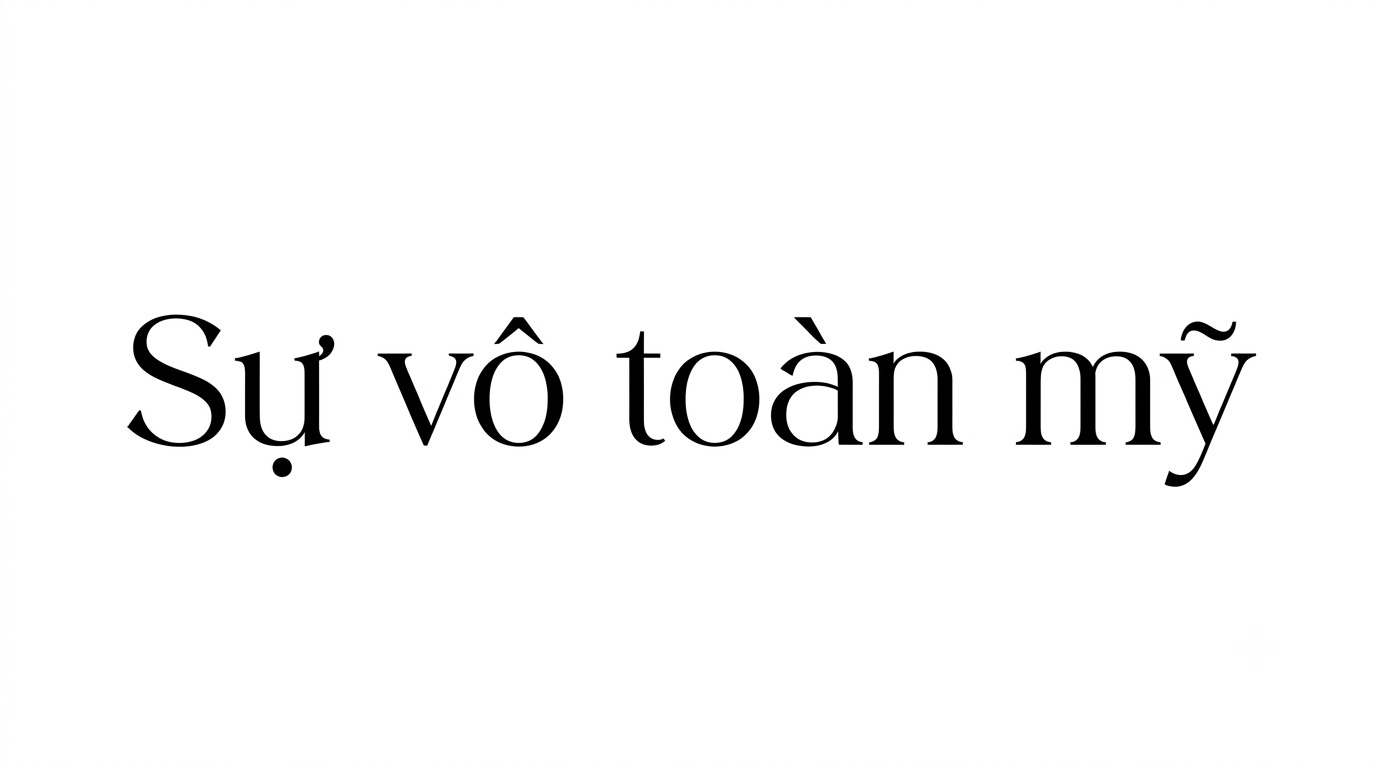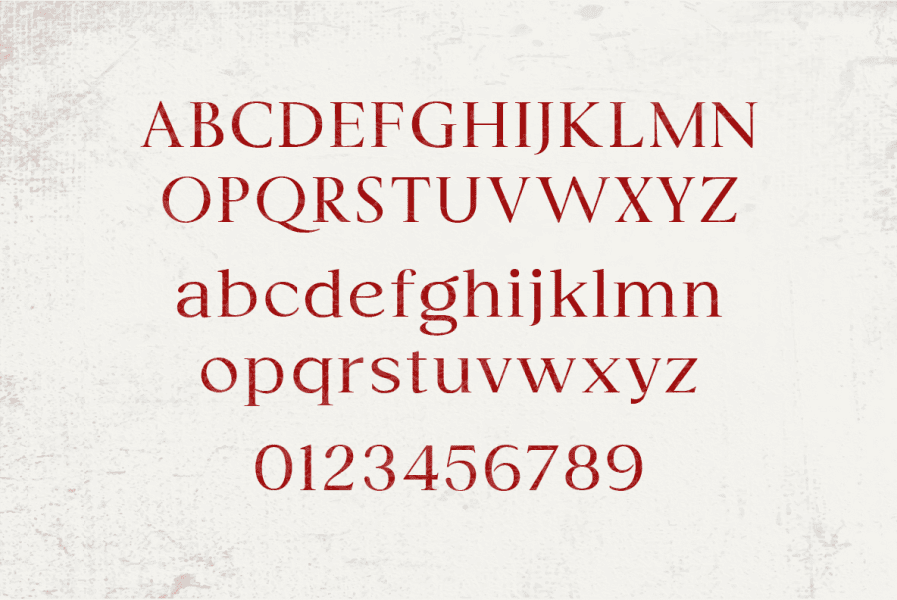
Tải 5+ bộ font Việt hóa Menata sắc nét chuyên thiết kế bao bì sang trọng
Designer khi sử dụng font Menata thường gặp tình trạng thiếu dấu tiếng Việt, sai ký tự hoặc nét chữ bị vỡ khi phóng lớn để in thiệp cưới, hộp mỹ phẩm và bao bì quà tặng. Những lỗi này có thể làm giảm tính thẩm mỹ của thiết kế và ảnh hưởng đến hình ảnh chuyên nghiệp của thương hiệu.
Font Menata là gì?
Menata là một phông chữ Serif (có chân) mang phong cách hiện đại, thanh lịch và đầy tính nghệ thuật. Phông chữ này là sự giao thoa giữa nét cổ điển quý tộc và cấu trúc hình học đương đại. Đặc điểm nhận diện của Menata là các đường nét được trau chuốt tỉ mỉ, độ tương phản giữa nét thanh và nét đậm cực kỳ tinh tế, tạo nên một cảm giác sang trọng, cao cấp cho mọi văn bản.
Trong lĩnh vực thiết kế thương hiệu, Menata thường được ưu tiên sử dụng cho các nhãn hàng thời trang cao cấp, mỹ phẩm, trang sức hoặc các dịch vụ spa nghỉ dưỡng 5 sao. Tuy nhiên, bản gốc của Menata thường không hỗ trợ đầy đủ các ký tự tiếng Việt có dấu. Bản font việt hóa Menata tại Xưởng In Viva đã được xử lý kerning chuẩn xác, thiết kế lại các dấu thanh (huyền, sắc, hỏi, ngã, nặng) sao cho hài hòa với phom chữ gốc, giúp các designer tại Việt Nam tự tin triển khai các dự án bao bì quà tặng mà không lo lỗi font.
Bảng kí tự font Menata
Lưu ý: Font Menata có cấu trúc nét thanh rất mỏng. Khi sử dụng cho mục đích in Offset trên các loại giấy nhám như giấy Kraft, bạn nên tăng nhẹ độ dày Stroke để đảm bảo chữ không bị mất nét do độ thấm mực của giấy.
5 ứng dụng của font Menata Việt hóa trong thiết kế và in ấn
Vẻ đẹp thanh lịch và hiện đại của Menata giúp các sản phẩm bao bì, quà tặng doanh nghiệp trở nên tinh tế hơn khi kết hợp cùng các kỹ thuật in ấn và gia công phù hợp:
• Thiết kế bao bì mỹ phẩm và hộp quà yến sào: Menata phù hợp để thể hiện tên thương hiệu trên nắp hộp cứng, hộp giấy cao cấp. Khi kết hợp cùng kỹ thuật ép kim, dập nổi hoặc phủ UV định hình, font chữ này giúp tạo điểm nhấn sang trọng cho sản phẩm.
• Sản xuất túi giấy thương hiệu thời trang: Sử dụng Menata cho logo, slogan hoặc tên bộ sưu tập trên túi giấy Ivory, giấy mỹ thuật giúp thương hiệu thể hiện phong cách tinh tế, phù hợp với các dòng sản phẩm hướng đến phân khúc cao cấp.
• In ấn quà tặng gốm sứ tri ân đối tác: Logo hoặc thông điệp sử dụng font Menata khi in nung trên bộ ấm chén sứ tạo cảm giác trang nhã, phù hợp với các mẫu quà tặng doanh nghiệp dành cho khách hàng và đối tác.
• Khắc laser bình giữ nhiệt và sổ tay da: Các đường nét chữ Menata khi khắc trên kim loại, da hoặc gỗ có thể tạo điểm nhấn cá nhân hóa cho các sản phẩm quà tặng như bình giữ nhiệt, bút ký, sổ tay doanh nhân.
• Thiết kế thiệp cưới, voucher và ấn phẩm sự kiện: Với phong cách mềm mại, Menata phù hợp để trình bày tiêu đề, tên khách mời, lời chúc hoặc thông điệp trên thiệp cưới, voucher cao cấp và các ấn phẩm sự kiện.
Font Menata đẹp 01
5 lưu ý khi sử dụng font chữ Menata Việt hóa
Để font Menata giữ được vẻ đẹp thanh lịch khi chuyển từ file thiết kế sang sản phẩm thực tế, designer cần chú ý các yếu tố kỹ thuật sau:
• Kiểm soát độ mảnh của nét chữ: Menata có các chi tiết chữ thanh mảnh. Khi in trên giấy Kraft, giấy mỹ thuật có bề mặt nhám hoặc tem nhãn kích thước nhỏ, nên kiểm tra kích thước chữ để hạn chế tình trạng mất nét do mực thấm vào bề mặt giấy.
• Tối ưu đường Path cho gia công dập nổi: Khi sử dụng Menata làm logo trên hộp cứng, file vector cần được xử lý các điểm neo và đường cong nhỏ. Việc tối ưu path giúp khuôn dập tái hiện rõ các chi tiết chữ, hạn chế ảnh hưởng đến phần mép giấy trong quá trình gia công.
• Điều chỉnh khoảng cách ký tự (Kerning): Với các cụm từ tiếng Việt có nhiều dấu như dấu hỏi, dấu ngã hoặc dấu nặng, designer nên tinh chỉnh khoảng cách giữa từng ký tự để bố cục logo và tiêu đề trở nên cân đối hơn.